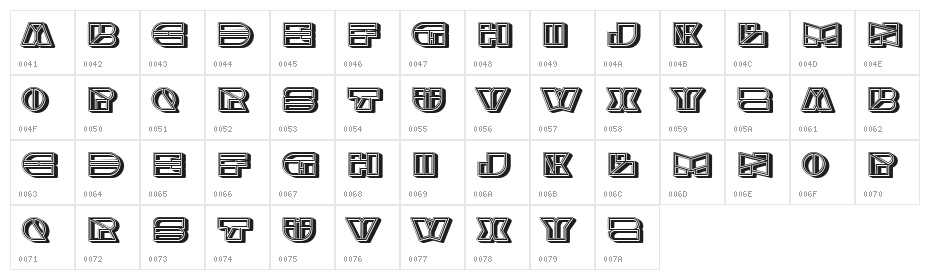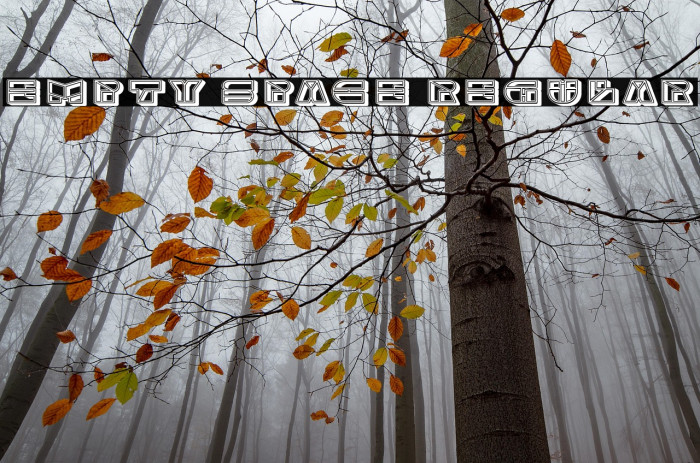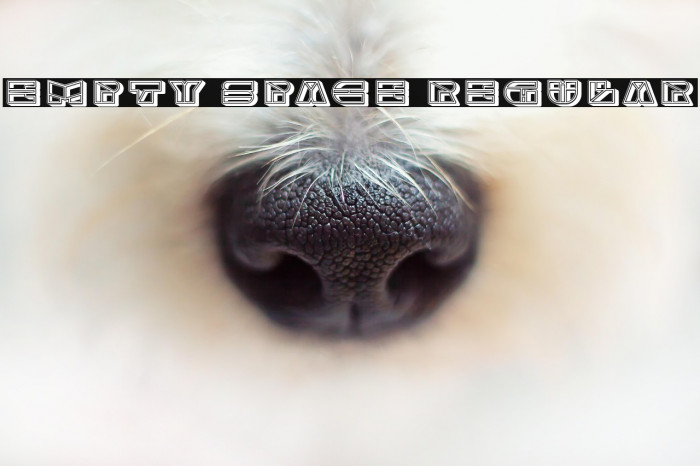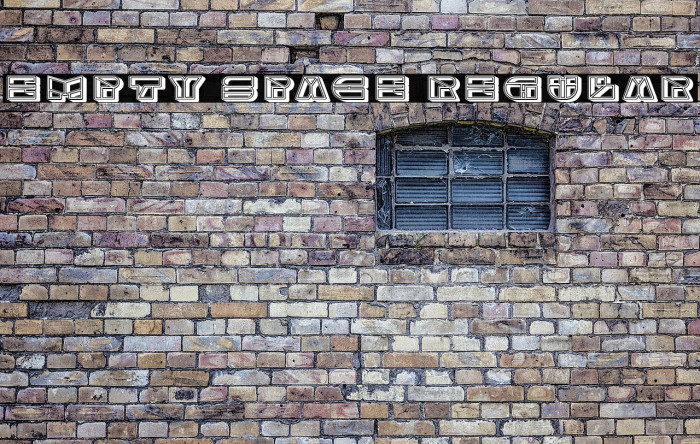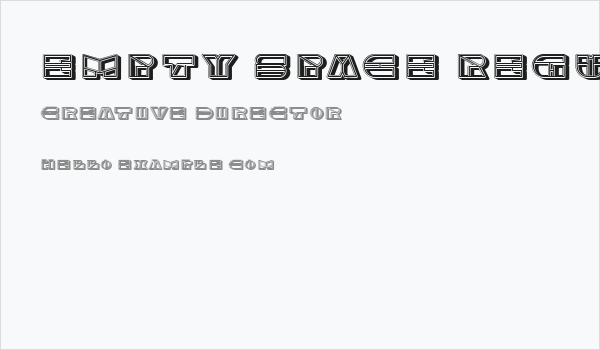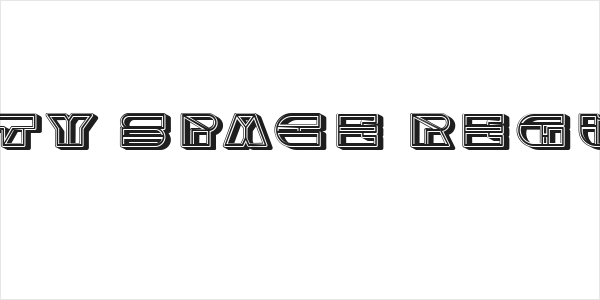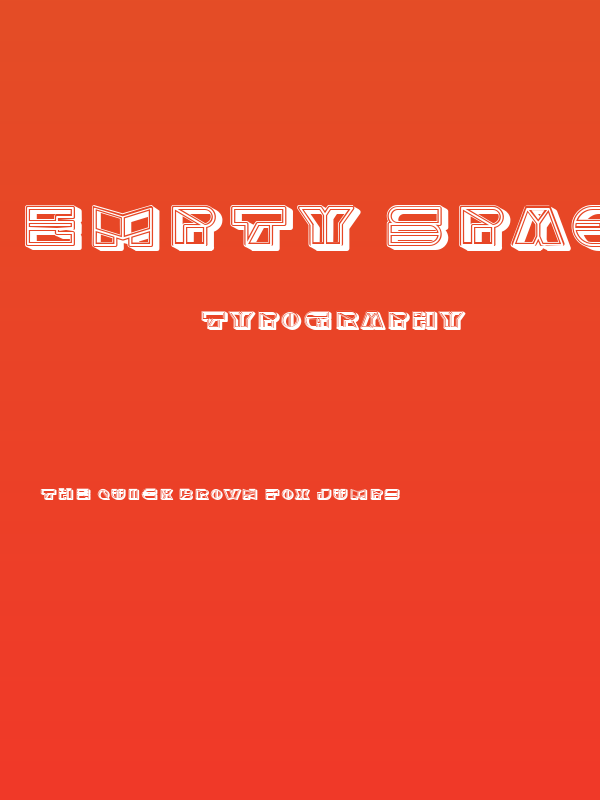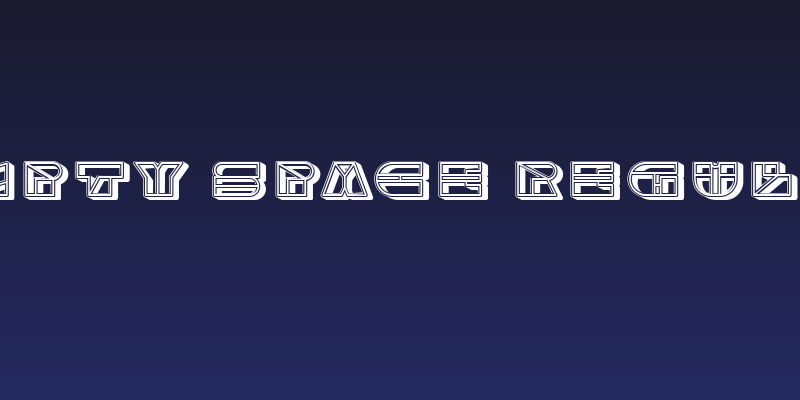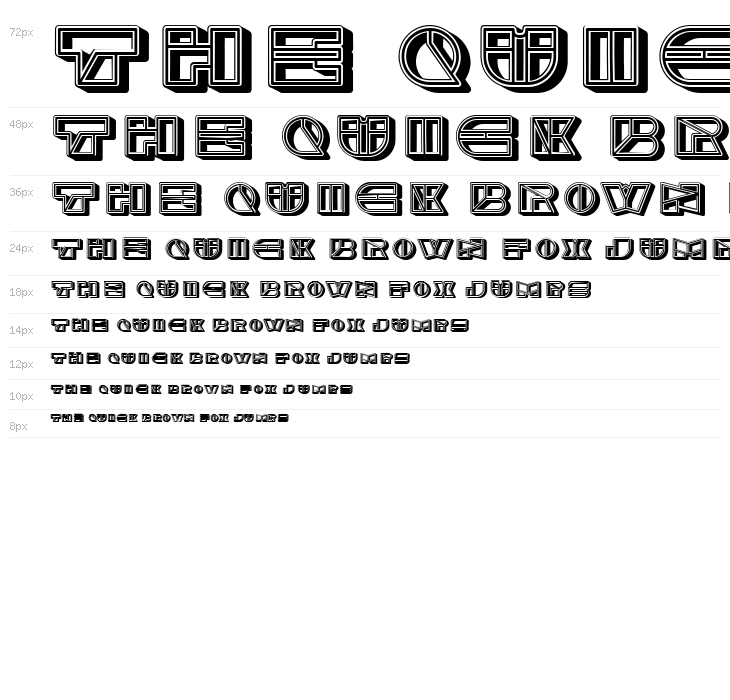
Empty Space Regular Font
| Estilo general | Futuristic, Decorative |
| Proyectos propuestos | Ideal for sci-fi themed designs, posters, branding, and any project needing a futuristic and bold typeface. |
Empty Space Regular